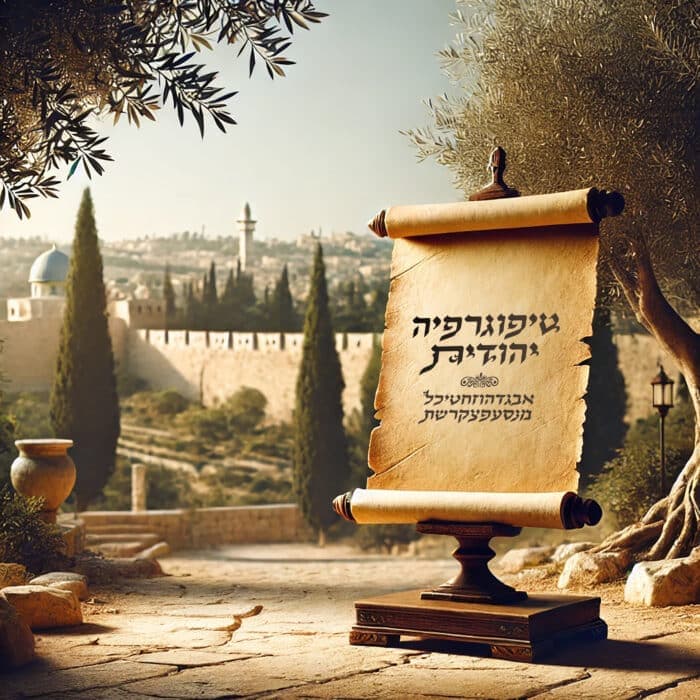
טיפוגרפיה יהודית היא לא רק אוסף אותיות, כי אם הרבה הרבה מעבר: זו שפה חזותית עשירה המשקפת היסטוריה, תרבות ואמונה עמוקה – והכל באמצעות אותיות.
שורשיה של טיפוגרפיה זו נטועים עמוק בכתבים הקדומים, בראשם הכתב העברי המקראי וכתב רש"י, שהשפיעו באופן משמעותי על עיצוב הפונטים בשפה העברית המודרנית.
המאמר הנוכחי יעמיק בשורשי הטיפוגרפיה היהודית ויבחן את השפעת הכתבים הקדומים על עיצוב פונטים בעולם המודרני של היום.
הכתבים המקובלים מימות הקדמונים, ביניהם כתב רש״י והכתב העברי המופיע במקרא, היוו את הבסיס ואת הכר הפורה לפיתוח טיפוגרפיה יהודית.
כתבים אלה התאפיינו במבנה ייחודי של האותיות, בקישוטים ובסגנונות כתיבה מאד מגוונים. המאפיינים הללו השפיעו על האופן שבו אנו תופסים את הכתב העברי כיום.
הכתב העברי המקראי הוא הכתב המקורי שבו נכתבו התורה והנביאים. הוא התאפיין בפשטות ובבהירות, והיה מיועד לקריאה בקול רם, הנראות והעיצוב שלו סייעו להקראה נהירה.
כתב רש"י היה כתב ידני שפותח על ידי רבי שלמה יצחקי או בשמו המוכר והנפוץ יותר: רש"י. תוכלו גם לכנות אותו מעצב הפונטים היהודי הראשון בעולם. כתב זה התאפיין בקו עגול יותר ובקישוטים מורכבים, ועשו בו שימוש נרחב בעולם היהודי במשך מאות שנים.
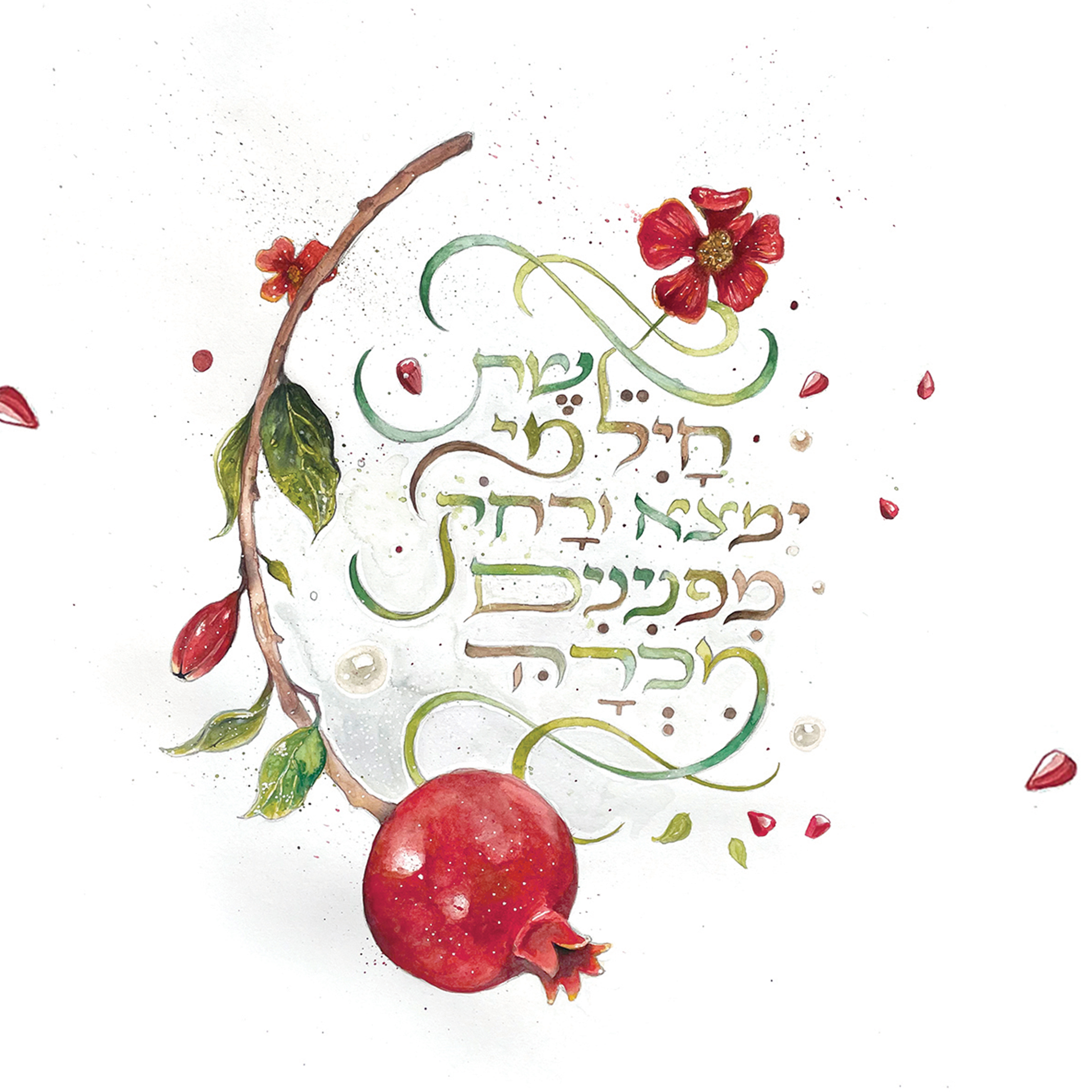
הכתבים הקדומים השפיעו על עיצוב פונטים בעברית עם ניקוד במגוון דרכים. ראשית, הם השפיעו על המבנה הבסיסי של האותיות, על היחסים בין האותיות השונות ואפילו על המרווחים ביניהן.
בנוסף, הם גם היוו השראה לסגנונות השונים של הפונטים, ביניהם פונטים מסורתיים, פונטים מודרניים ואף פונטים עיצוביים.
שלישית, הם השפיעו על השימוש בקישוטים בפונטים והיוו תשתית לעיצוב פונטים מקושטים ובעלי אופי לא סטנדרטי.
כיום מופיעים ברחבי הרשת הרבה סוגים של פונטים בעברית להורדה, רבים מהם מושפעים מהכתבים הקדומים.
ניתן למצוא טיפוגרפיה יהודית מגוונת עם ובלי ניקוד בסגנונות שונים, החל מפונטים קלאסיים המבוססים על הכתבים הקדומים ועד לפונטים מודרניים המשלבים אלמנטים עיצוביים חדשניים ביותר.
טיפוגרפיה יהודית אף פעם לא הפסיקה להתפתח ולהתחדש, ועודנה ממשיכה לעשות זאת במאה ה-21. עם התפתחות הטכנולוגיה ובעזרתה, קיימים כיום מגוון רחב של פונטים מומלצים בעברית, בין אם פונטים חינמיים ובין אם כאלה מסחריים.
מעצבים גרפיים רבים משתמשים באפשרויות שהיא מציעה כדי ליצור עיצובים ייחודיים ומקוריים, בעלי אופי מרשים ובעיקר מסוים ואחר.
טיפוגרפיה יהודית היא תחום עשיר ומורכב, המשלב היסטוריה, תרבות ואמנות. הכתבים הקדומים היוו את הבסיס לפיתוח טיפוגרפיה כפי שאנחנו מכירים אותה כיום, והשפיעו באופן משמעותי, עמוק, וכזה שאי אפשר להתעלם ממנו או להתכחש לו על עיצוב פונטים מודרניים בשפה העברית.
היכרות עם השורשים ההיסטוריים שלה עוזרת לנו להעריך את מורכבותה ואת יופייה, ואף להישען עליה וללמוד מנה רבות לגבי עיצוב והעברת מסר באמצעות צורניות של כתב.
לשימור מסורת טיפוגרפיה יהודית בעיצוב פונטים מודרניים יש חשיבות רבה מכמה סיבות:
הטכנולוגיה המודרנית שיחקה תפקיד משמעותי בהתפתחות זו. בעזרת תוכנות מתקדמות לעיצוב גרפי, מדפסות דיגיטליות ואמצעים דיגיטליים חדשנים נוספים, נוצרו אפשרויות כמעט בלתי מוגבלות לעיצוב פונטים חדשים ויצירתיים.
התוצאה היא מגוון עצום של פונטים בשפה העברית. בנוסף, הטכנולוגיה מקלה משמעותית על ההפצה והנגישות של פונטים, ומאפשרת למעצבים מכל העולם להשתמש בהם.